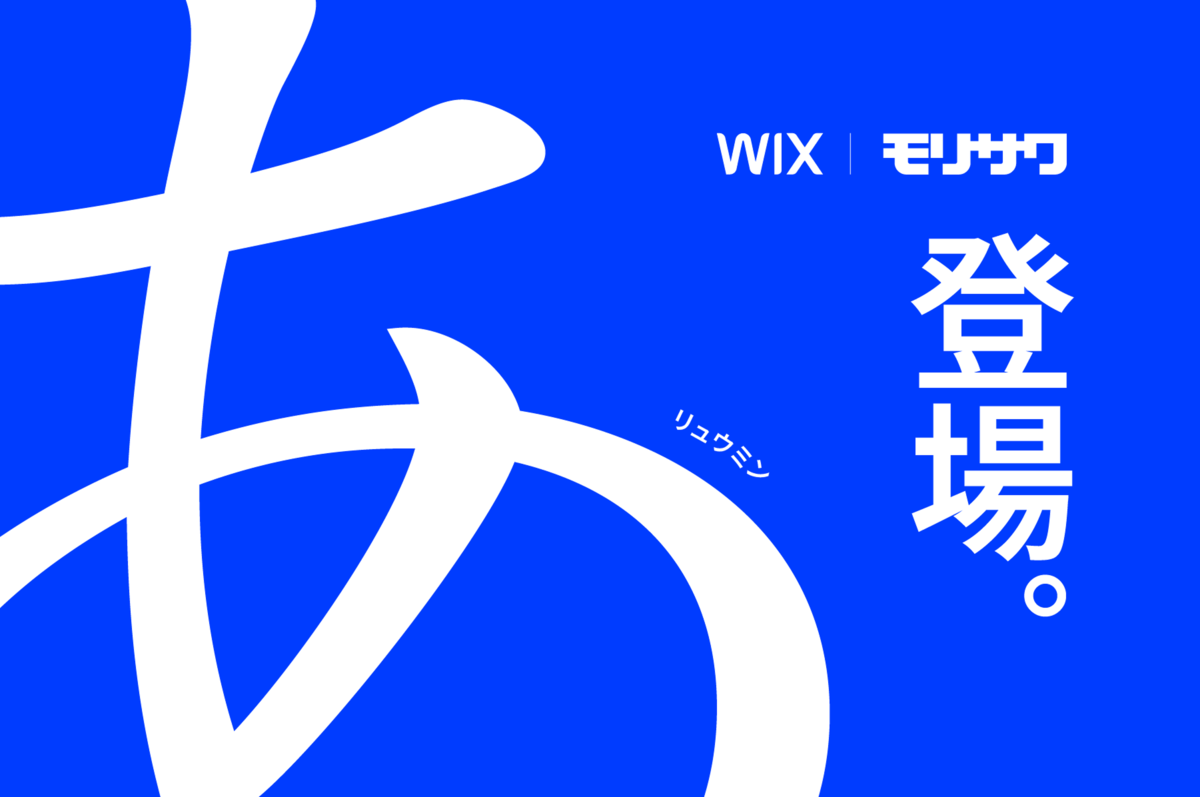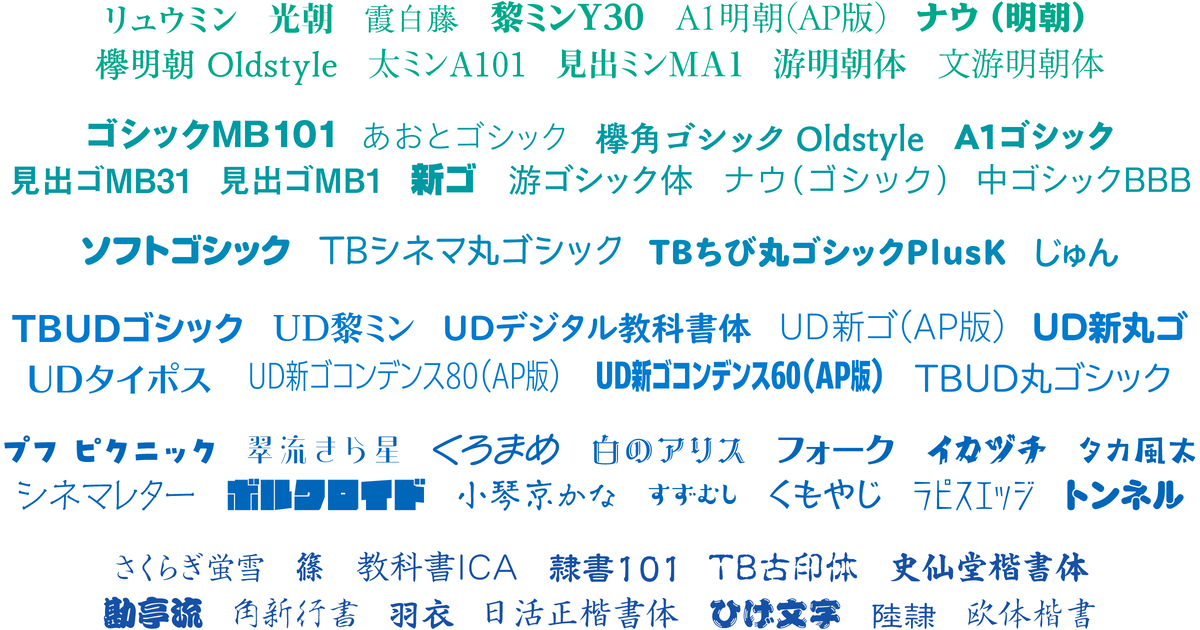
モリサワがWeb制作プラットフォーム「Wix」へUD新ゴやA1ゴシック、リュウミンなどプロ愛用の日本語フォント200書体を提供開始
モリサワは、世界有数のSaaS型Web制作プラットフォーム「Wix.com Ltd.(NASDAQ: WIX 以下、Wix)」に、UD新ゴやA1ゴシック、リュウミンなど多くのプロデザイナーに愛用いただいている人気書体を含む日本語フォント200書体の提供を開始したことを発表した。
今回、日本でのサービス浸透とともに日本語のフォント拡充のニーズが高まり、モリサワのフォントが採用。
提供した200書体は、書籍や広告でも使われる可読性の高い明朝体やゴシック体に加え、ゲーム、コミック、アニメ、YouTubeの字幕といったさまざまなシーンで活躍する人気のデザイン書体など、バラエティーに富んだラインナップとなる。
加えてWebアクセシビリティの観点からもニーズが高まっているユニバーサルデザイン(UD)フォントもお使いいただけます。今回のフォント提供により、日本語を使ったWebデザインの自由度が大幅に向上し、より魅力的なWebサイトを作成できる。
▼提供書体
※画像内の書体は提供書体の一部。
フォントの充実は日本のユーザー様、パートナー様から寄せられていた長年の要望でした。モリサワ様の高品質な日本語フォントがWixの制作プラットフォームに統合されることで、より優れたWebサイトの制作体験が実現しました。日本のタイポグラフィを牽引するモリサワ様との提携を誇りに思い、Wixユーザーの皆様が自由に表現できる環境を提供できることを嬉しく思います。今後も私たちは、日本のお客様のニーズに応え、皆様のオンラインでの成功を支援してまいります。
今回のフォント提供により、Wixユーザーの皆様の、より豊かなWebサイト制作環境の実現に貢献できることを嬉しく思います。Webサイトのデザインやコンテンツは多様化しており、それに伴い、フォントの重要性も増しています。プロデザイナーを中心に幅広い方にご愛用いただいているモリサワの日本語Webフォントを使用いただくことで、サイトの個性をより際立たせ、ブランドイメージを向上させることができます。Wix様の優れたWebサイト制作プラットフォームにて、ぜひ多彩なフォントデザインの違いを楽しんでいただけますと幸いです。